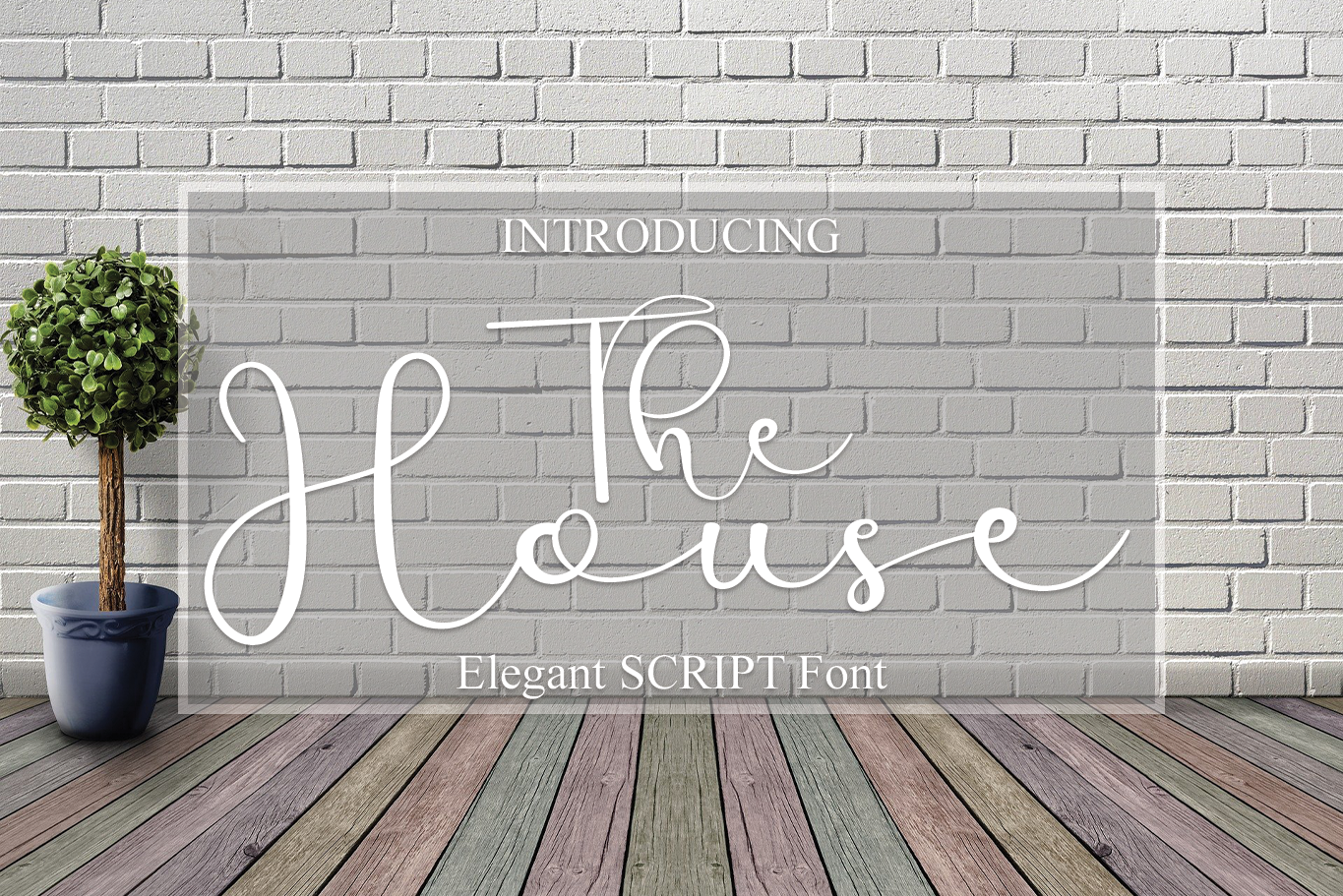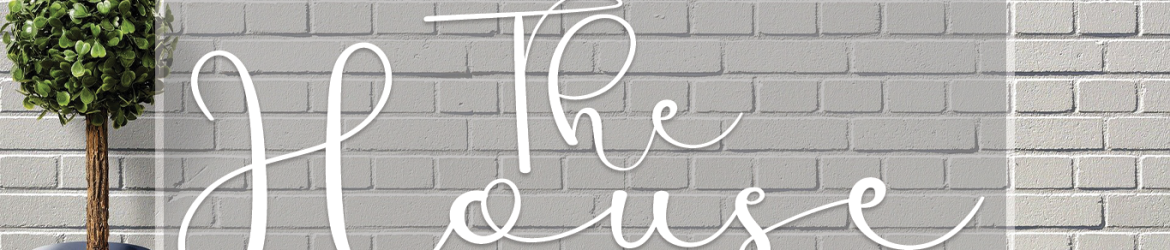
The House Font – Download Grátis
A fonte The House é uma delícia para os olhos com suas letras redondas e escrita a mão suave. Ela traz caracteres dançando ao longo do linha base, criando um toque de luxo que certamente enriquecerá qualquer projeto gráfico que você desejasse criar. A designer Erik Studio trouxe para nós uma ferramenta perfeita para quem busca um ar refinado e elegante em seus projetos, seja ele para assinatura, logomarca ou até mesmo para textos informativos. O The House é a escolha perfeita para aqueles que procuram dar um toque especial à sua identidade visual.